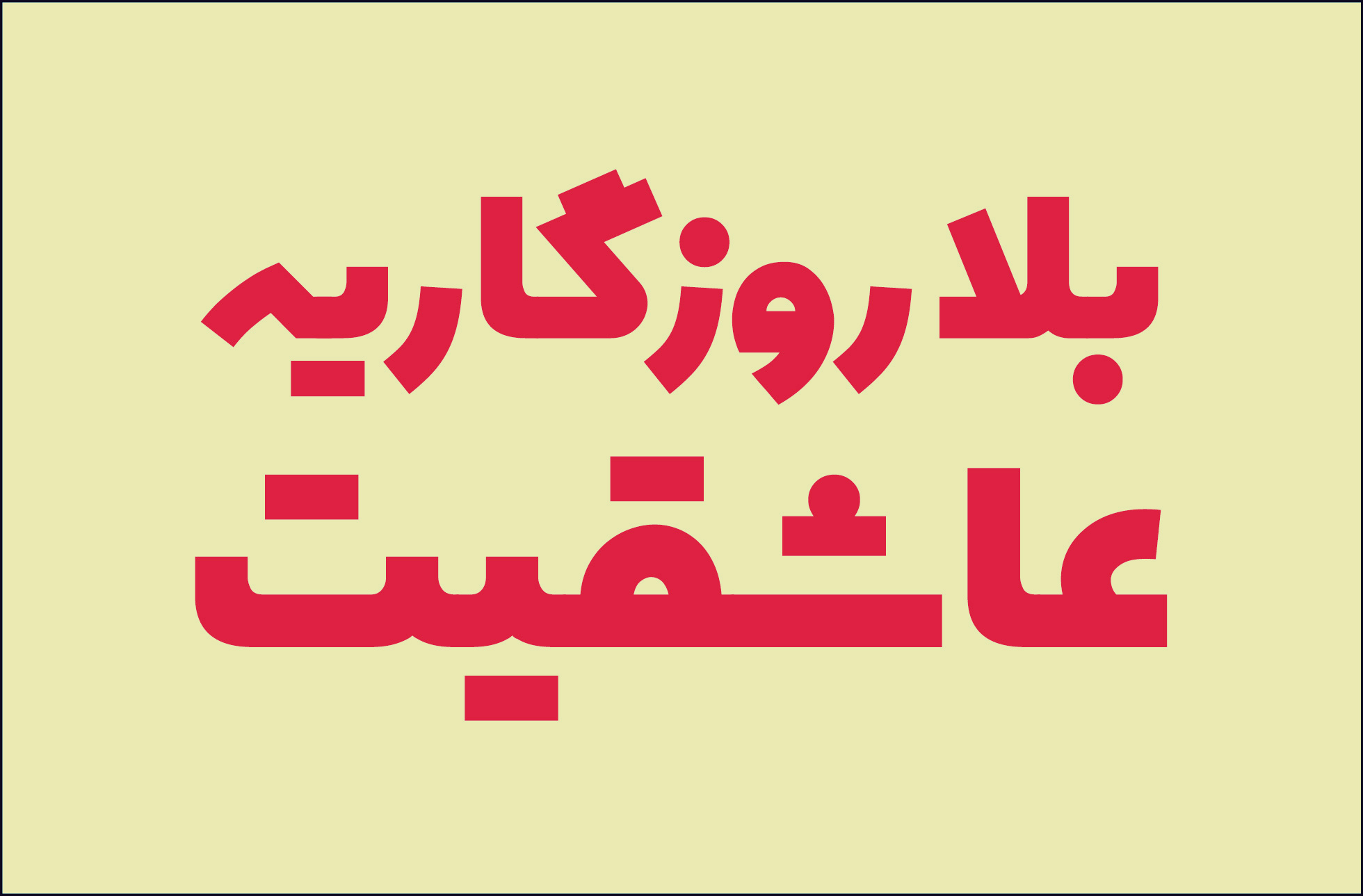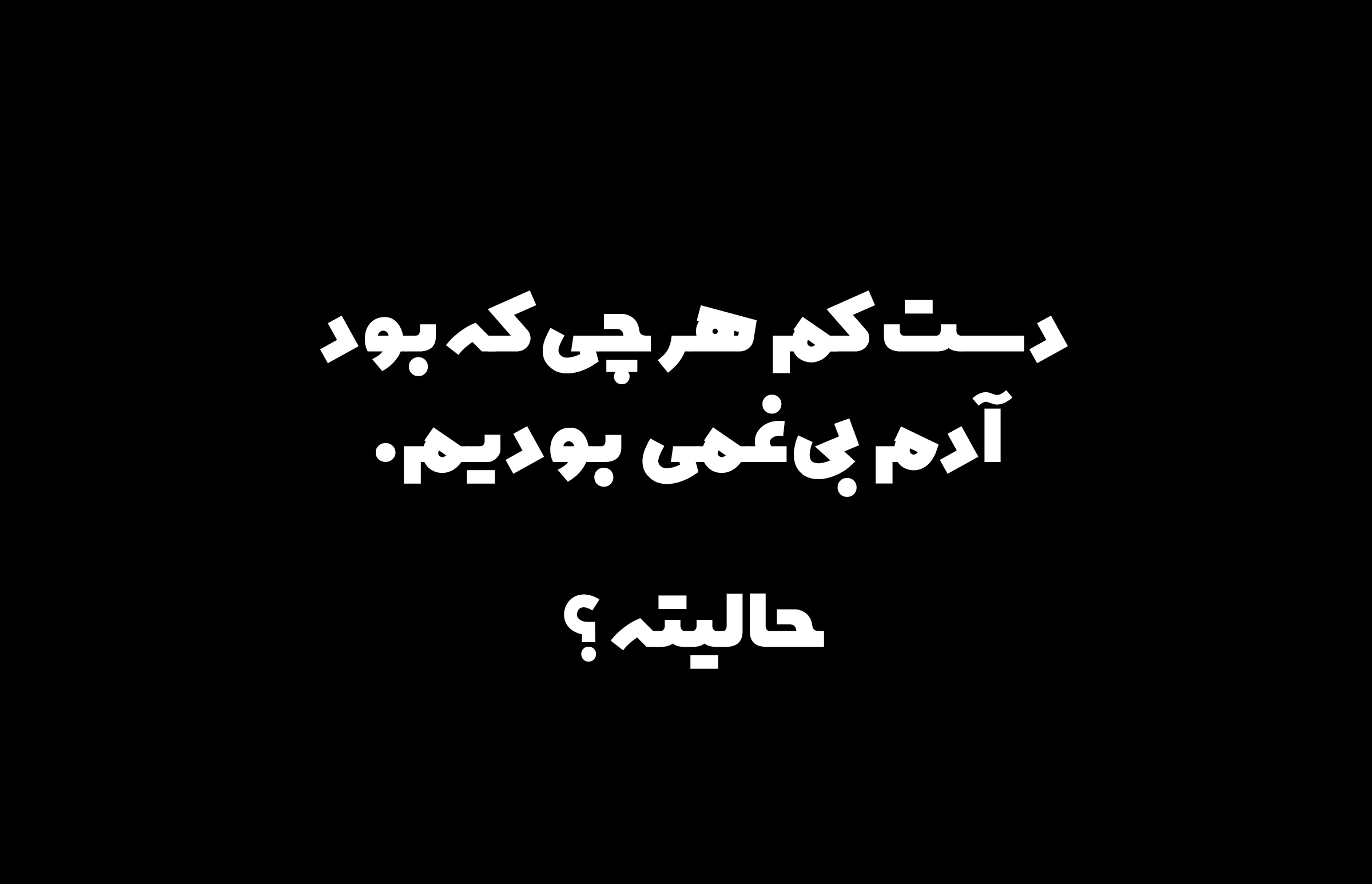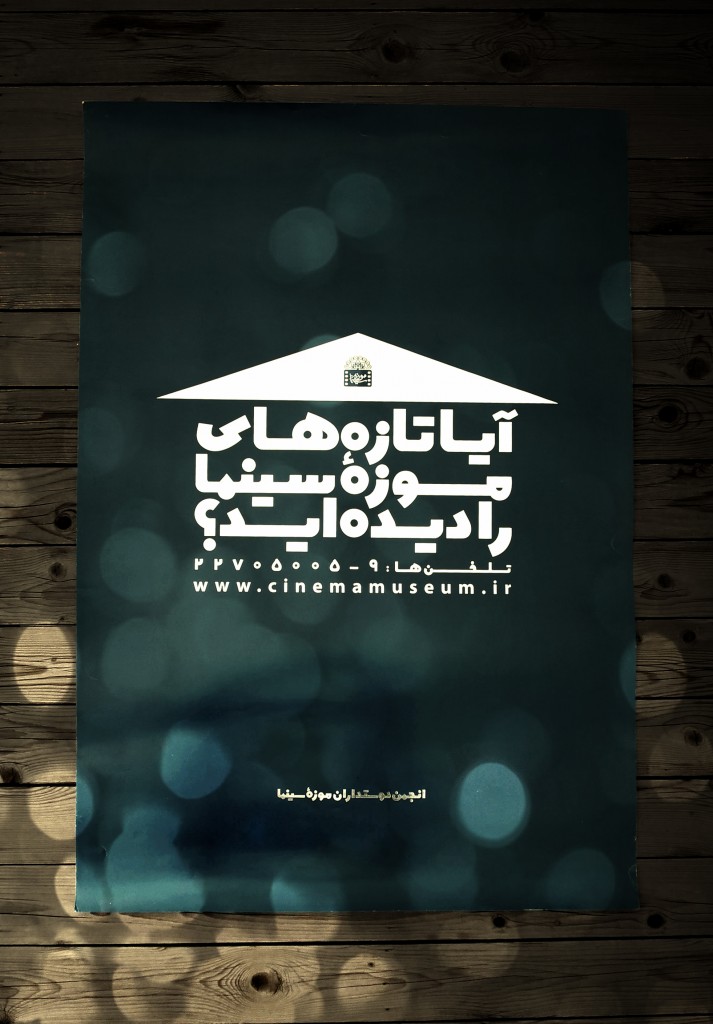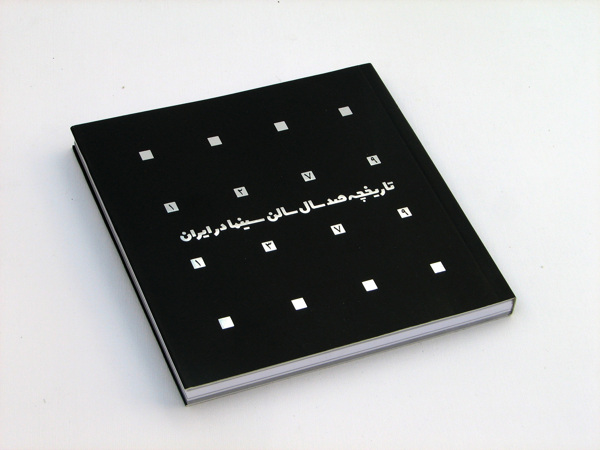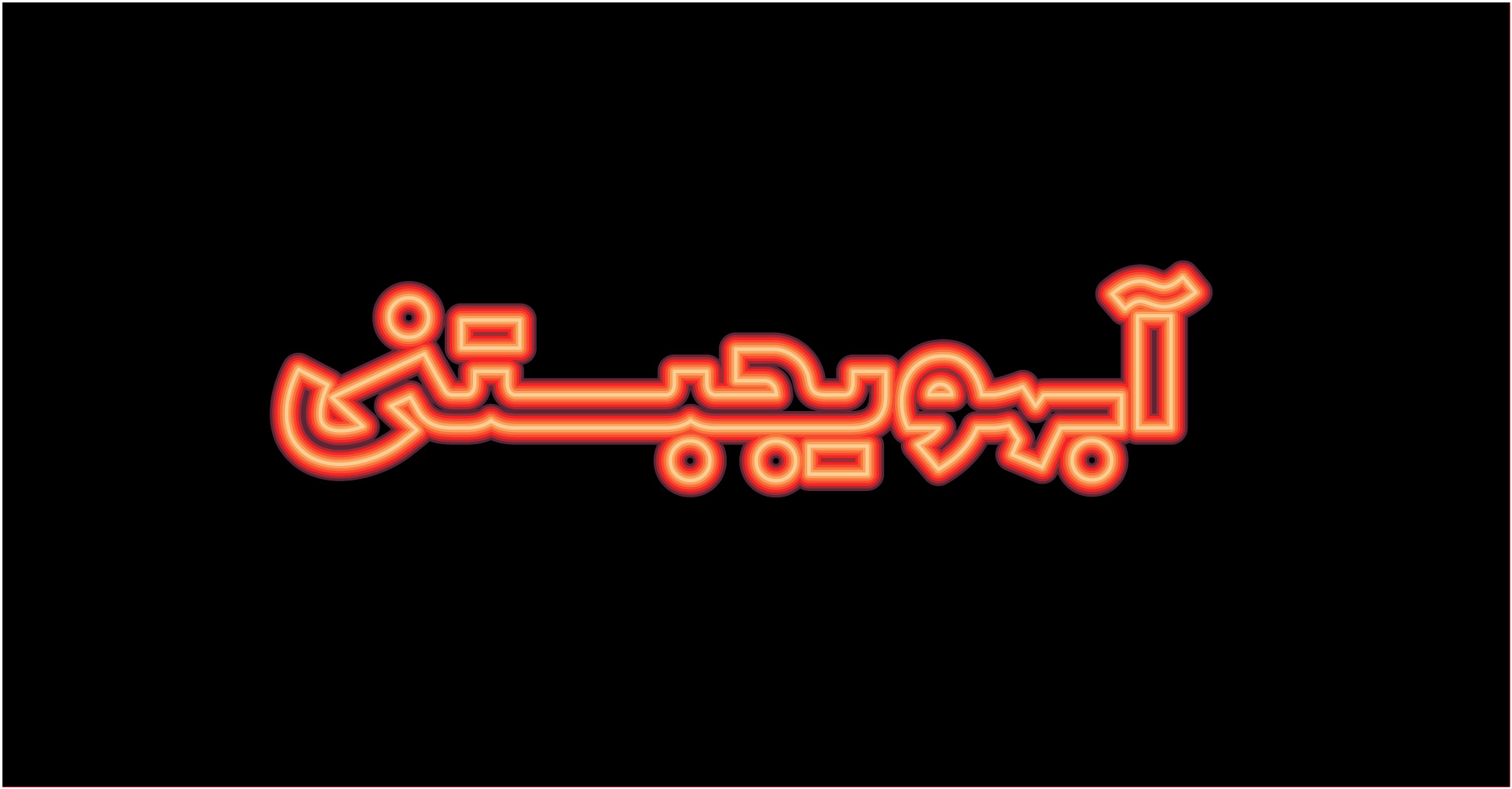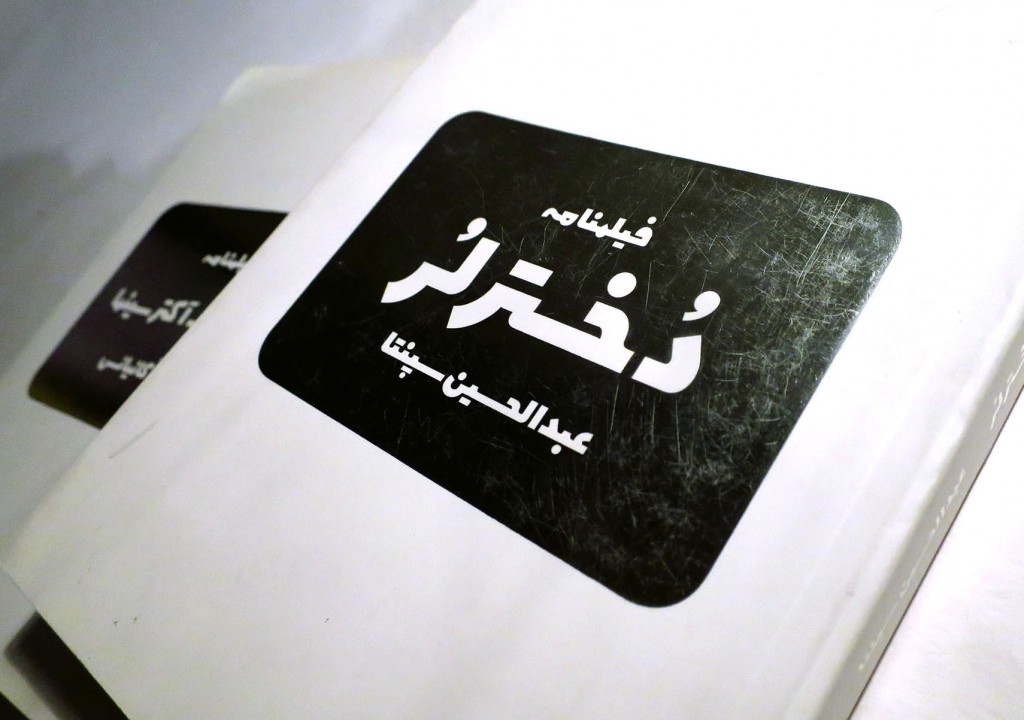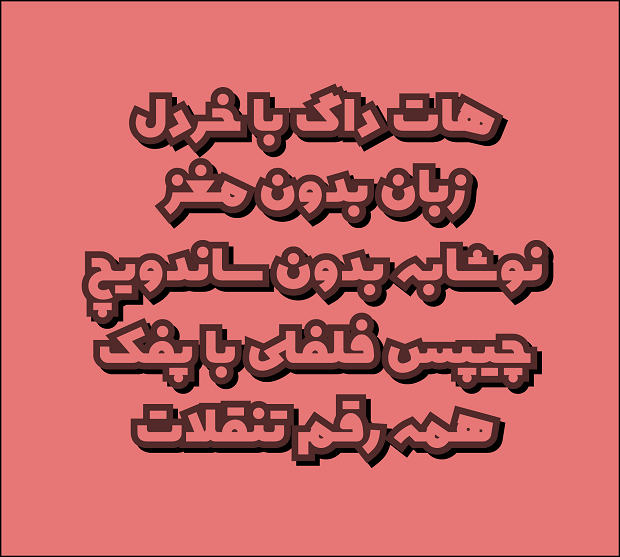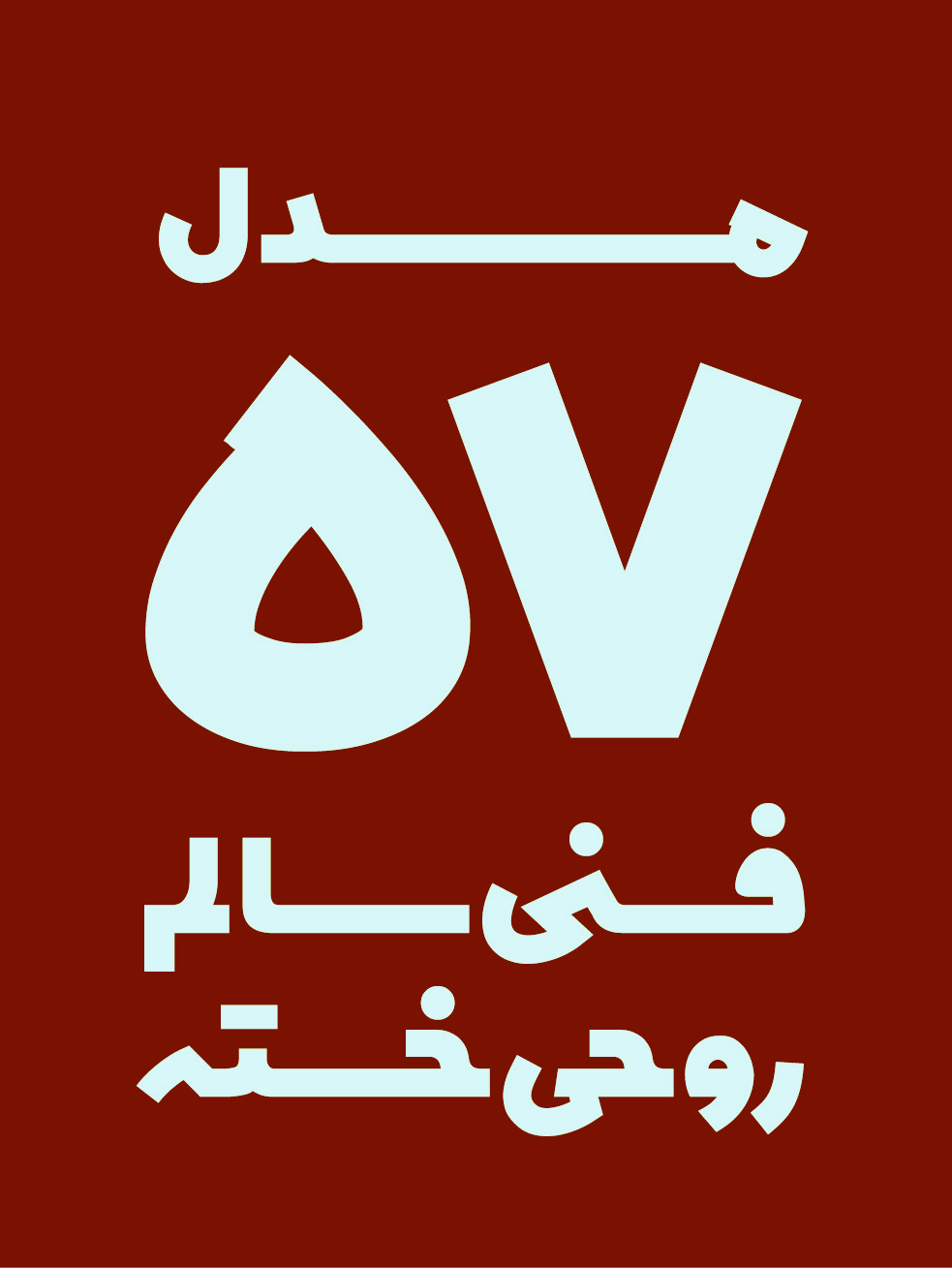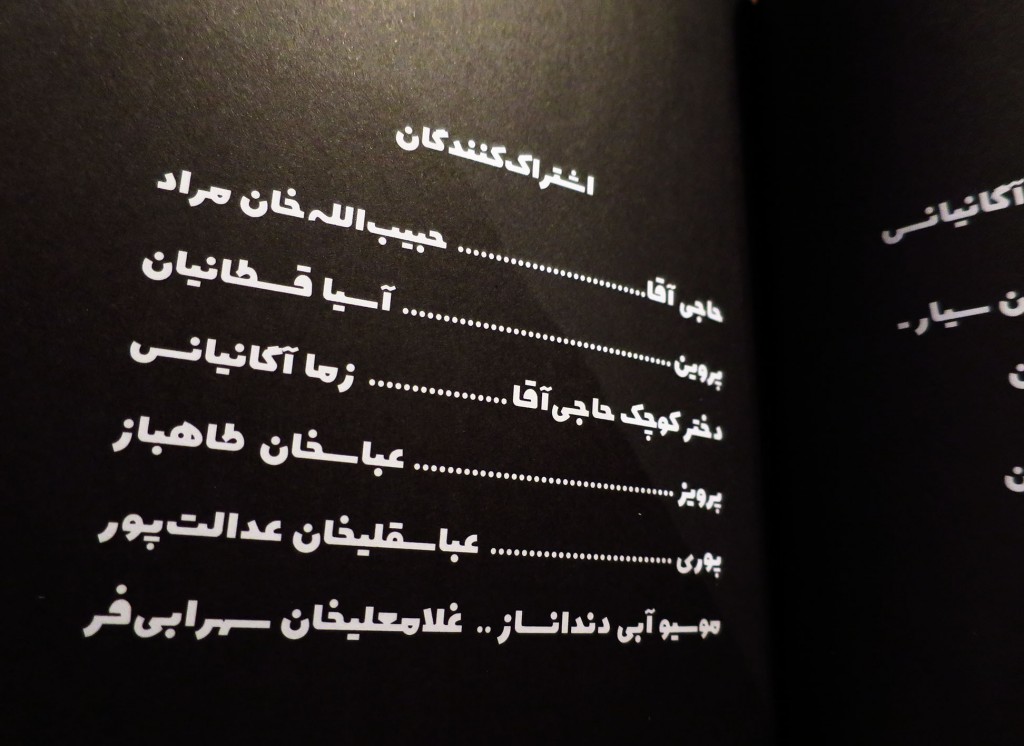
درباره قلم سینما
تولد شدن فونت سینما برمیگردد به سال ۸۷، زمانی که قرار شد کتاب “زرد مشکی” با طراحی گرافیک کوروش پارسانژاد را صفحهآرایی و عنوانبندیهای آن را بر اساس پوسترهای سینمایی قدیمی انجام دهم. برای انجام عنوانبندیها تصمیم گرفتم منطق مشترکی که بین بعضی از حروف پوسترهای قدیمی دیده میشد را شسته و رُفته استخراج کنم که در عمل، این حروف استخراج شده قابلیتهای خوبی برای عنوانهای کتاب بهوجود آوردند.
در طول کارِ کتاب به این حروف علاقهمند شدم. هوشمندیهای بهکار رفته در طراحی این حروف (که همه دستنویس یا بهتر بگویم دستکشیده بودند) من را با خودشان درگیر میکردند و ذهنم را به تجربیات خودم در سنین خیلی پایینتر (زمانی که فارغ از رسمالخطها و قواعد بودم) می بردند که اشکال حروف در اثر دیدن سر در سینماها و تابلوهای مغازههایی که هنوز سیل فلکسی-فیسها به آنها نرسیده بود در سرم ورز داده میشد و پیچ و تاب میخورد.
کمی قبلتر از این، تبدیل فونت دستنویس راشین خیریه برای استفاده در یکی از کتابهایش، بهانهای شد که با نرمافزارهای ایجاد فونت کار کنم و قلقهای کار دستم بیاید. وجود این تجربهها و داشتن تعداد زیادی از گلیفهای فونت سینما باعث شد تا تصمیم بگیرم کل حروف را تکمیل کنم و حروف استخراج شده را تبدیل به فونت کنم. کمی بعد هم سفارشهایی از موزه سینما داشتم که در آنها از این فونت بهخاطر تناسب فرمی و مفهومی آن با کارها استفاده کردم.
علی پزشک